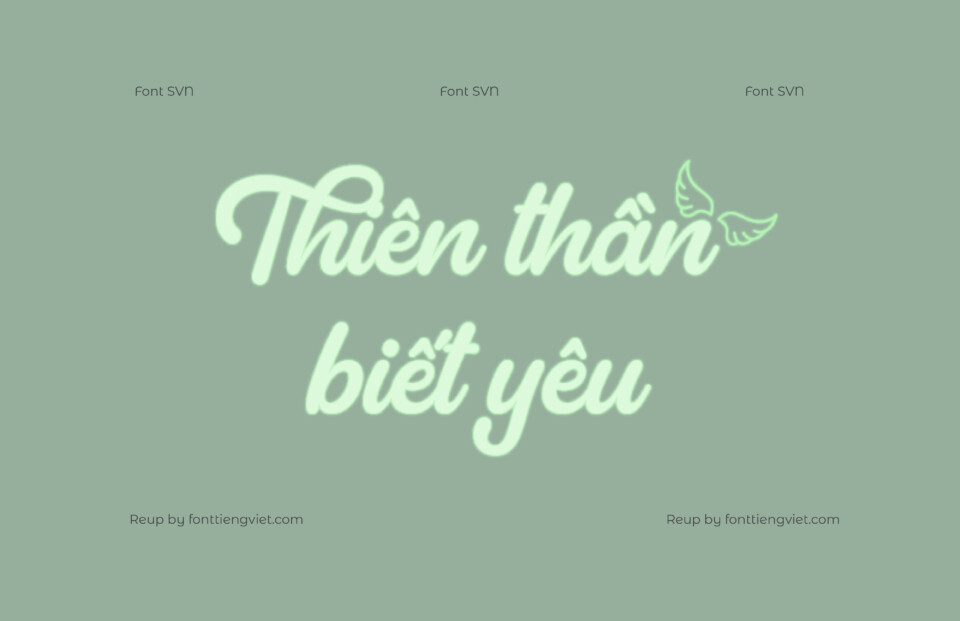
Font Việt hóa SVN Paula Natalie
Giới thiệu về Font Việt hóa SVN Paula Natalie
Trong thế giới đồ họa hiện đại, việc lựa chọn một Font Miễn Phí chất lượng luôn là ưu tiên hàng đầu của các nhà thiết kế. Font Việt hóa SVN Paula Natalie nổi lên như một lựa chọn hoàn hảo nhờ sự kết hợp tinh tế giữa nét chữ mềm mại và cấu trúc hiện đại. Đây là bộ phông chữ thuộc phong cách Script, mang đến cảm giác thủ công tự nhiên nhưng vẫn giữ được vẻ sang trọng, chuyên nghiệp cho mọi tác phẩm nghệ thuật.
Đặc điểm nổi bật của bộ font chữ này
Font Việt hóa SVN Paula Natalie sở hữu các đường nét thanh mảnh, uốn lượn cực kỳ uyển chuyển. Đặc biệt, phiên bản Việt hóa đã được tối ưu hóa hoàn toàn về dấu câu, giúp người dùng tại Việt Nam không còn lo lắng về lỗi hiển thị khi gõ tiếng Việt. Bộ font này cực kỳ phù hợp cho các dự án thiết kế thiệp mời đám cưới, bìa sách, logo thương hiệu cao cấp hoặc các biểu ngữ quảng cáo đòi hỏi tính thẩm mỹ cao và sự gần gũi.
Cách ứng dụng Font Việt hóa SVN Paula Natalie hiệu quả
Để phát huy tối đa vẻ đẹp của Font Việt hóa SVN Paula Natalie, bạn nên kết hợp nó với các font chữ không chân (Sans Serif) đơn giản. Sự tương phản này sẽ giúp nội dung chính trở nên nổi bật và dễ đọc hơn. Trong môi trường học đường, giáo viên và học sinh có thể sử dụng font này để trang trí các bài thuyết trình hoặc làm báo tường, tạo nên điểm nhấn sáng tạo và mới mẻ cho không gian học tập.
Lưu ý khi sử dụng trong thiết kế đồ họa